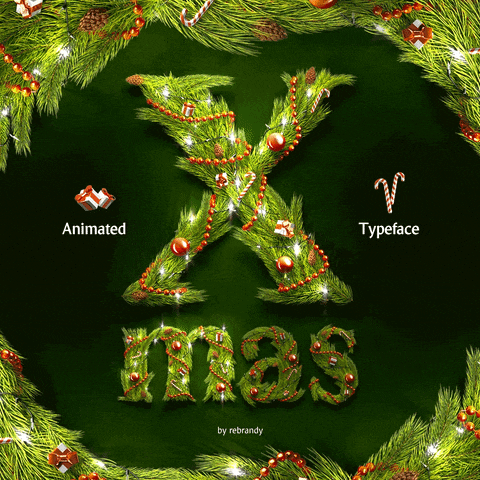
Название: Christmas Animated Typeface (2019)
Это полностью анимированный шрифт для Adobe Photoshop, в который мы поместили каждую ветку сосны, чтобы все 62 символа выглядели уникально. Новогодняя открытка на сайте, рассказы с решетками, привлекательная новостная рассылка по электронной почте - просто скажи слово.
Название: Christmas Animated Typeface (2019)
Это полностью анимированный шрифт для Adobe Photoshop, в который мы поместили каждую ветку сосны, чтобы все 62 символа выглядели уникально. Новогодняя открытка на сайте, рассказы с решетками, привлекательная новостная рассылка по электронной почте - просто скажи слово.